好看的404页面设计分享,总能让人甘愿迷失
如果说《歌手》在字体上的用心,是武装到了牙齿,那网页在404上的创意,可谓是填平了皱纹,让人挪不开眼,今天就一起来迷迷路~
替换式
最常见到就是在0上做文章,各种变换元素,让404有了不一样的主题感。
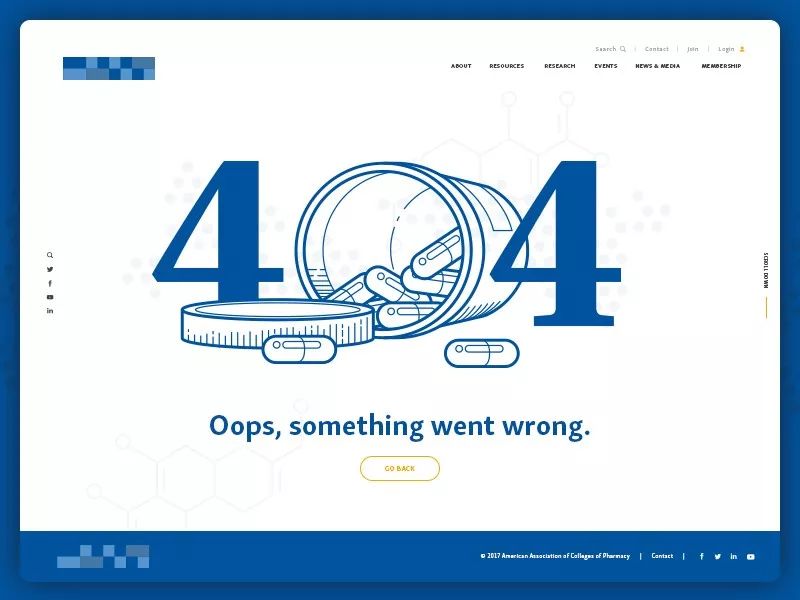
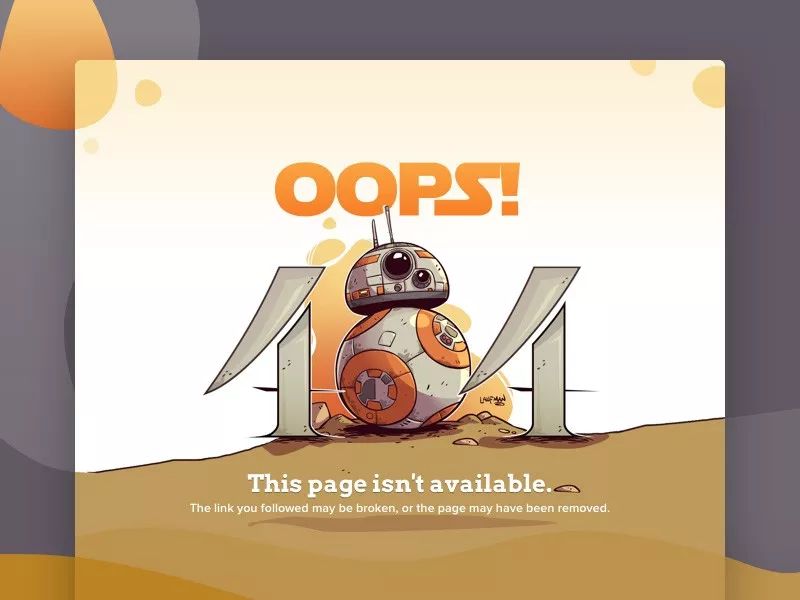
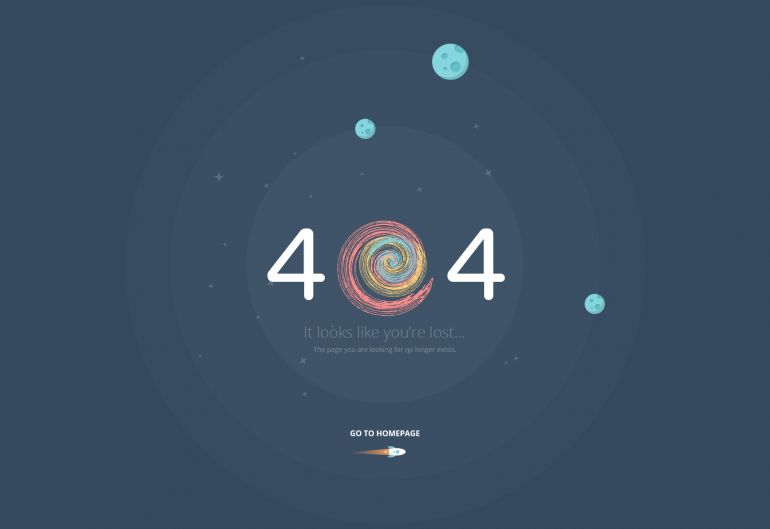
缠绕式
这种方法之前说过很多次了,什么来着,“蒙版擦,立体有”。
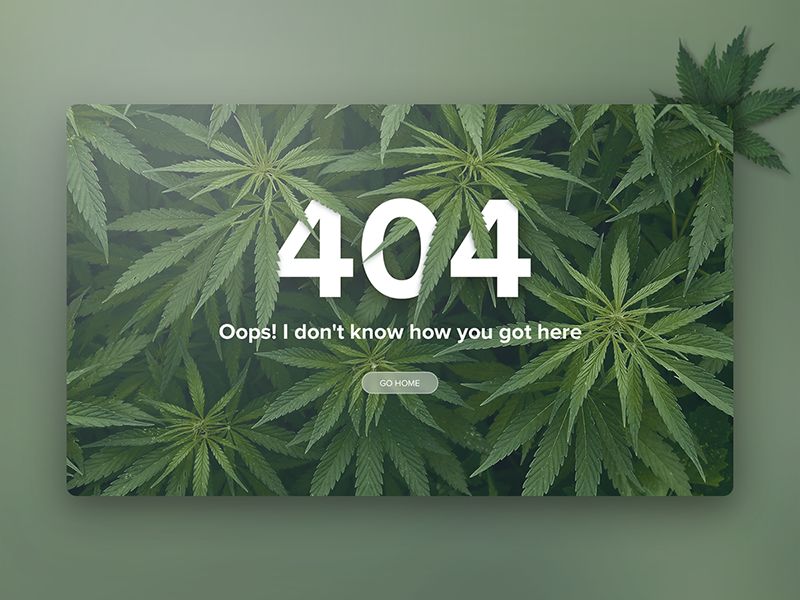
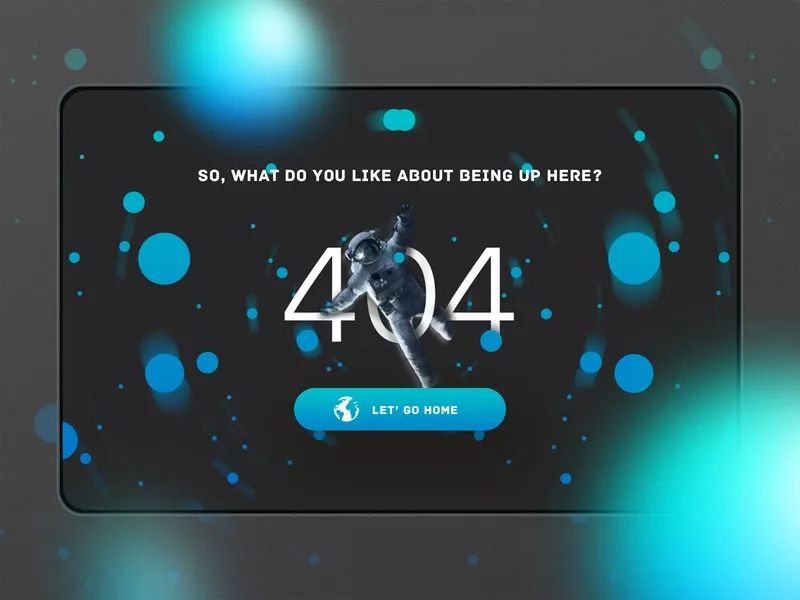
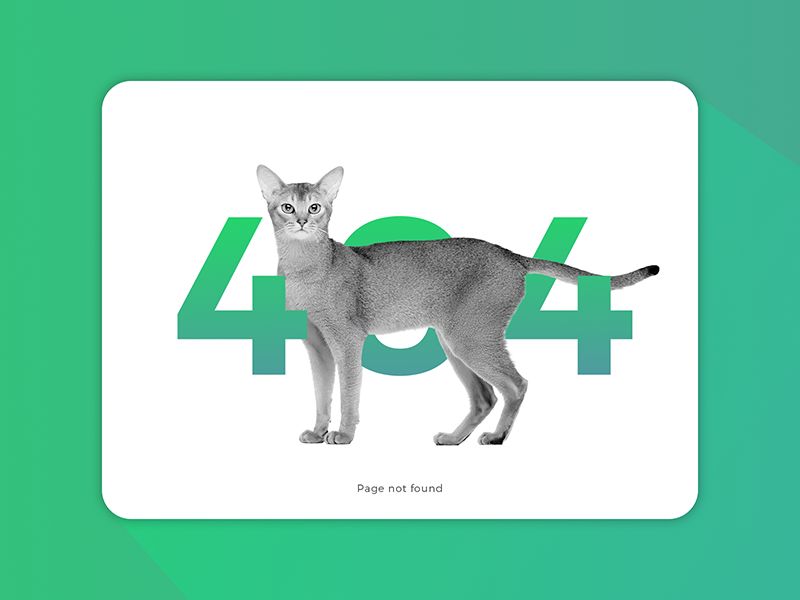
遮挡式
有缠绕,就有遮挡,都是为了增加立体感。
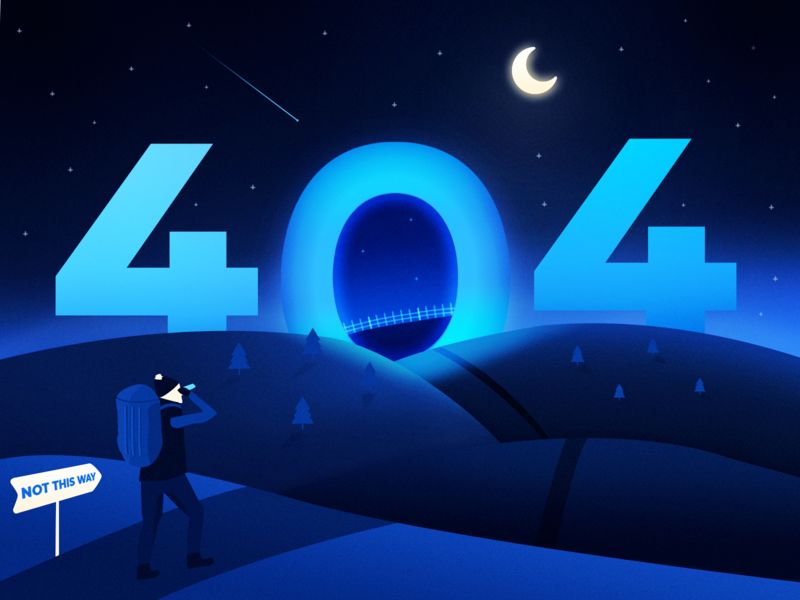
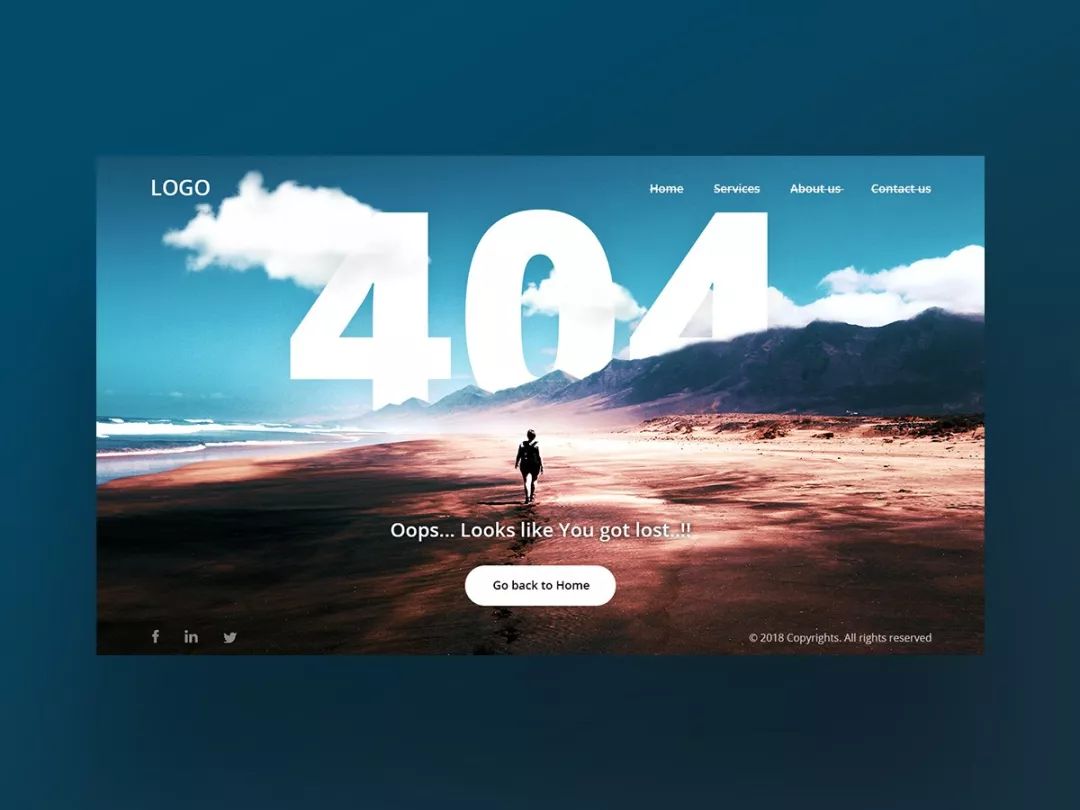
纹理式
用纹理表达404,能赋予其更多元素,看起来很活泼。
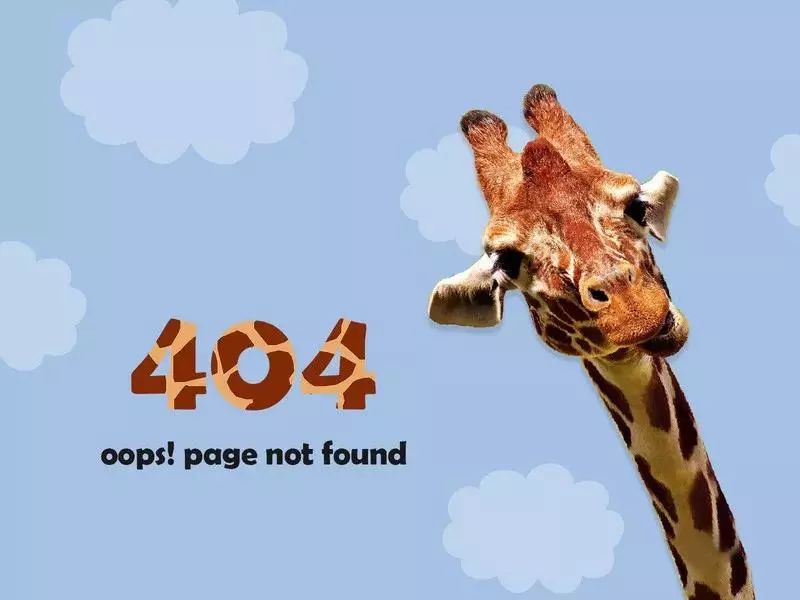
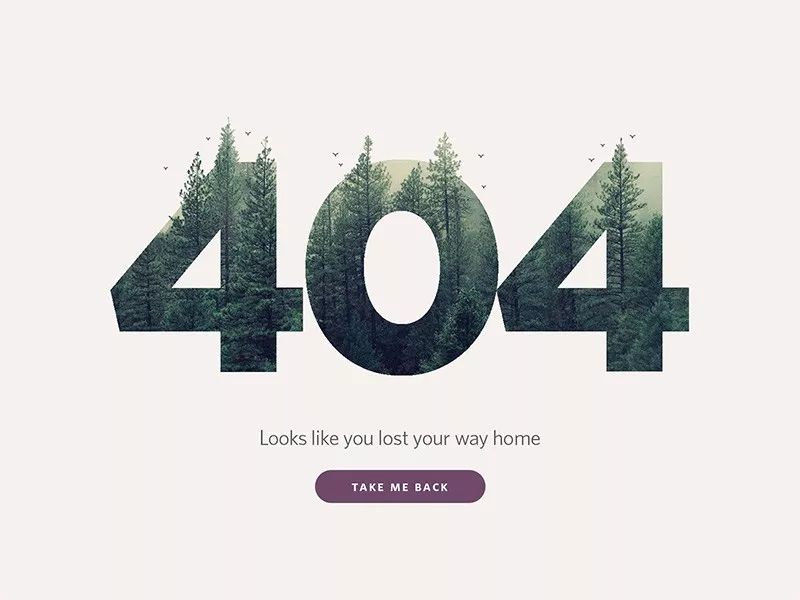
字效式
特效字你很熟悉了,只是如何让它看起来可盐可甜呢?
怎么样,今天的404玩得还尽兴吗?其实,能把大家都讨厌的东西,变得不讨厌,就是一种本事,对不,灭霸!